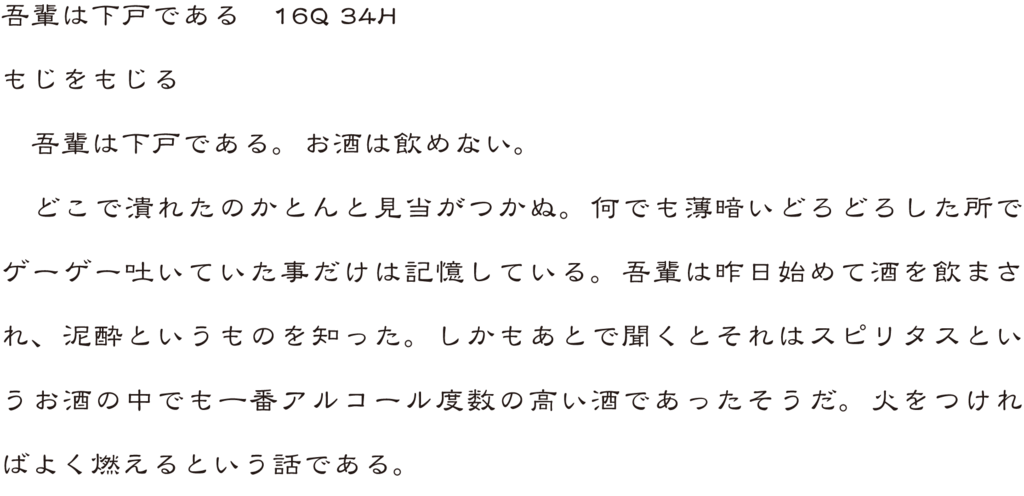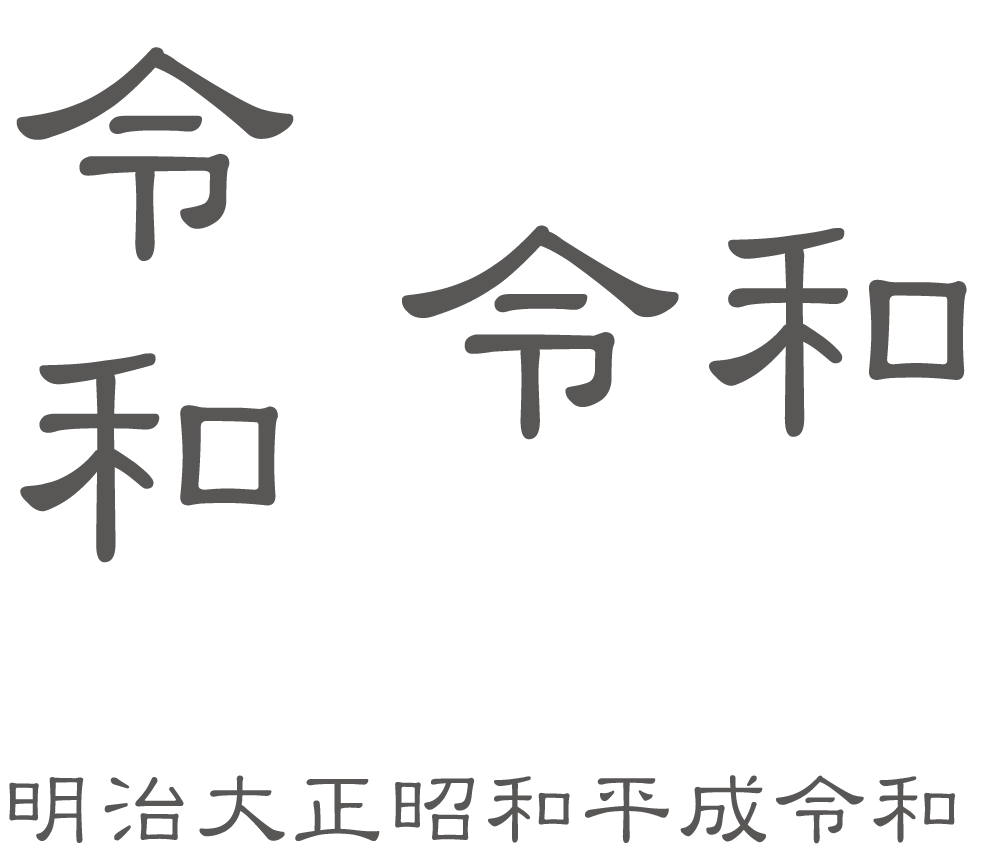
左右の払いが波を打っているようで横長な書体「隷書体」
隷書体の特徴は左右の払いが波を打っているようで横長な書体。
上記で使用した書体はダイナフォントの隷書体。
ダイナフォントの隷書体・DF隷書体
ダイナフォントの「隷書体」は楷書体に比べて素朴で落ち着いた雰囲気で幅広く平らな字形が特徴の書体。礼器碑、曹全碑、史晨前後碑、石門頌といった後世に伝えられた漢隷字体の書体をベースに開発されている。
また和文用仮名は「有限会社 字游工房」が制作を担当した。
ダイナフォントの隷書体・DF隷書体の組見本
新元号「令和」隷書体書体見本
新元号「令和」の隷書体の書体見本。